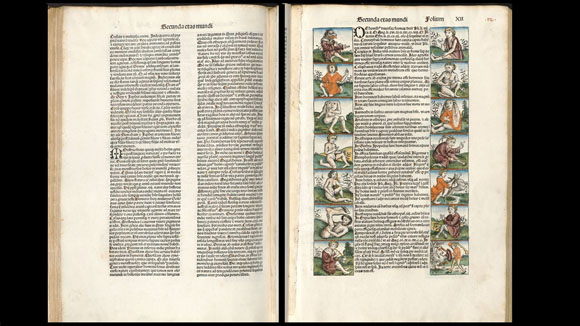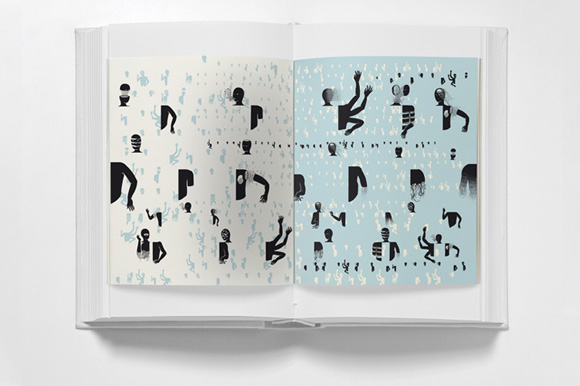
«Un tiempo antes del final: las páginas en blanco del Liber Chronicarum», es el nombre de la exposición que se presenta en la Biblioteca Nacional de España y en la que han colaborado la Escuela Superior de Diseño de Madrid, Ivorypress, el Museo della Carta e della Filigrana de Fabriano (Ancona, Italia) y la propia Biblioteca Nacional. En la misma se muestran ejemplares de las ediciones incunables de uno de los libros más importantes en la historia de la tipografía, el Liber Chronicarum (Crónicas de Nürenberg) a las que se contraponen la personal reelaboración del incunable realizada por alumnos de la ESD de Madrid. En este proyecto se han realizado fuentes tipográficas no alfabéticas, que permiten ilustrar el libro mediante tipos, a la manera en que se usaron las xilografías en su edición como bien explica Elizabeth Eisentein en su famoso libro «La revolución de la Imprenta en la edad moderna europea».